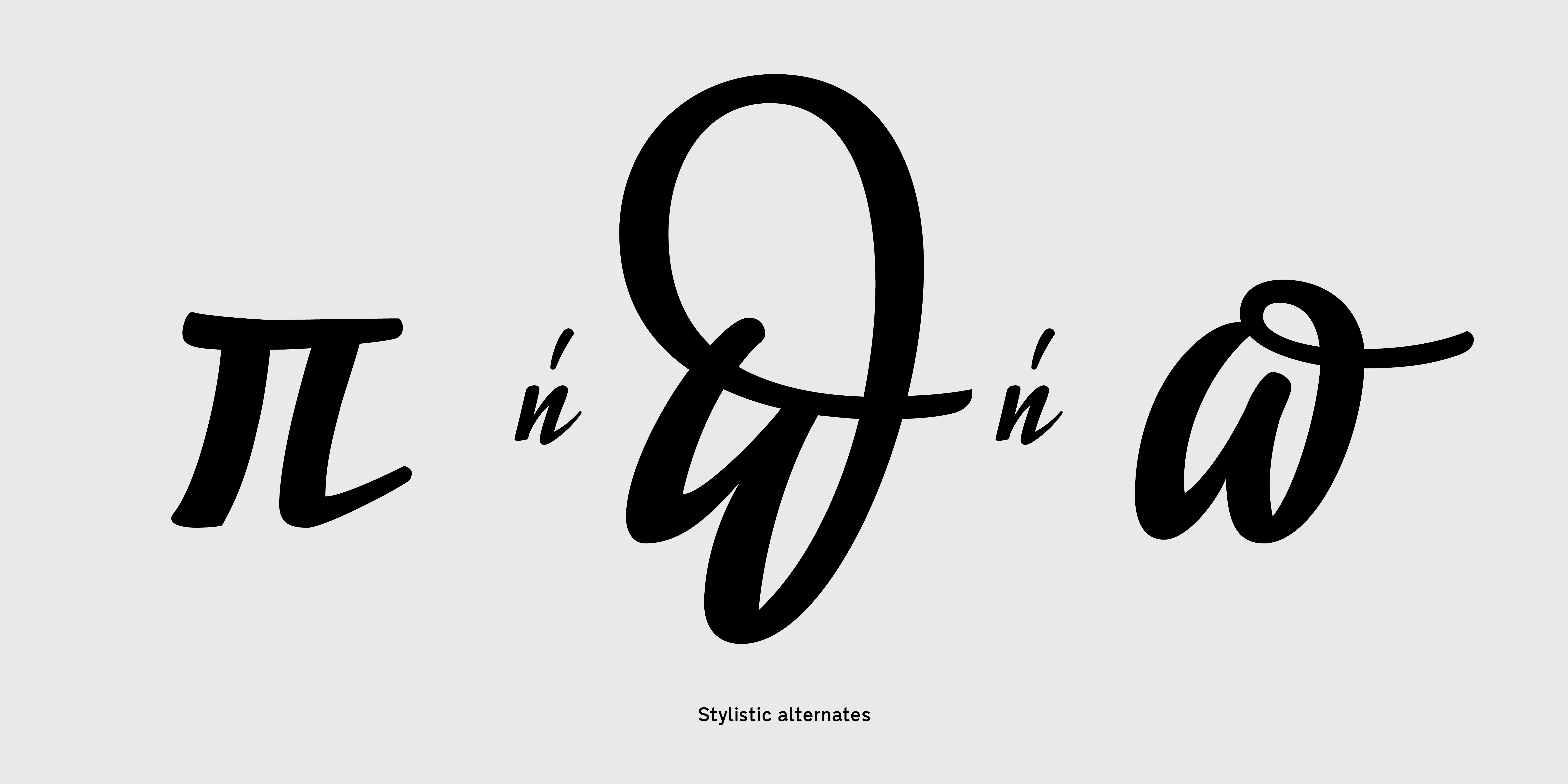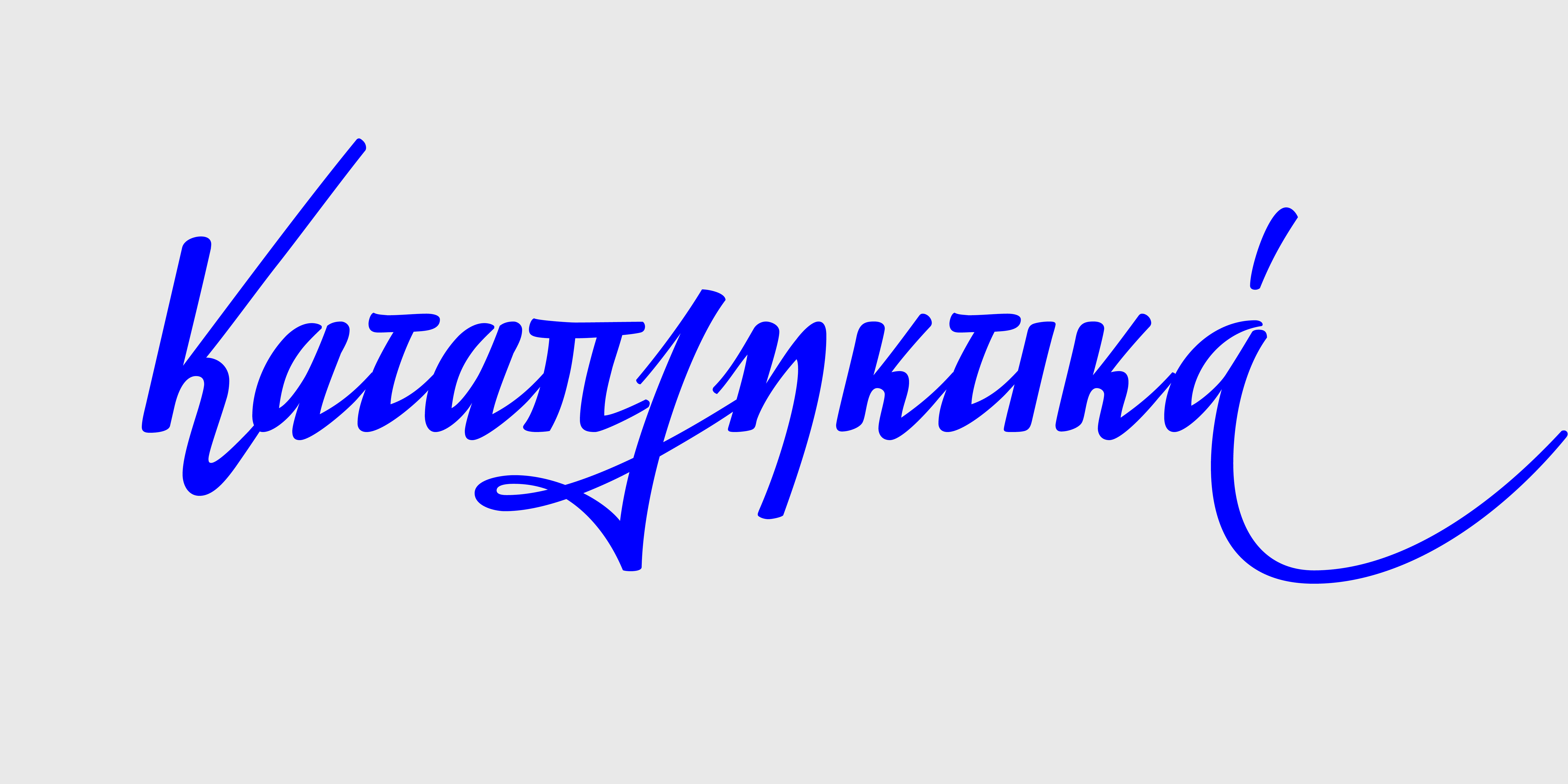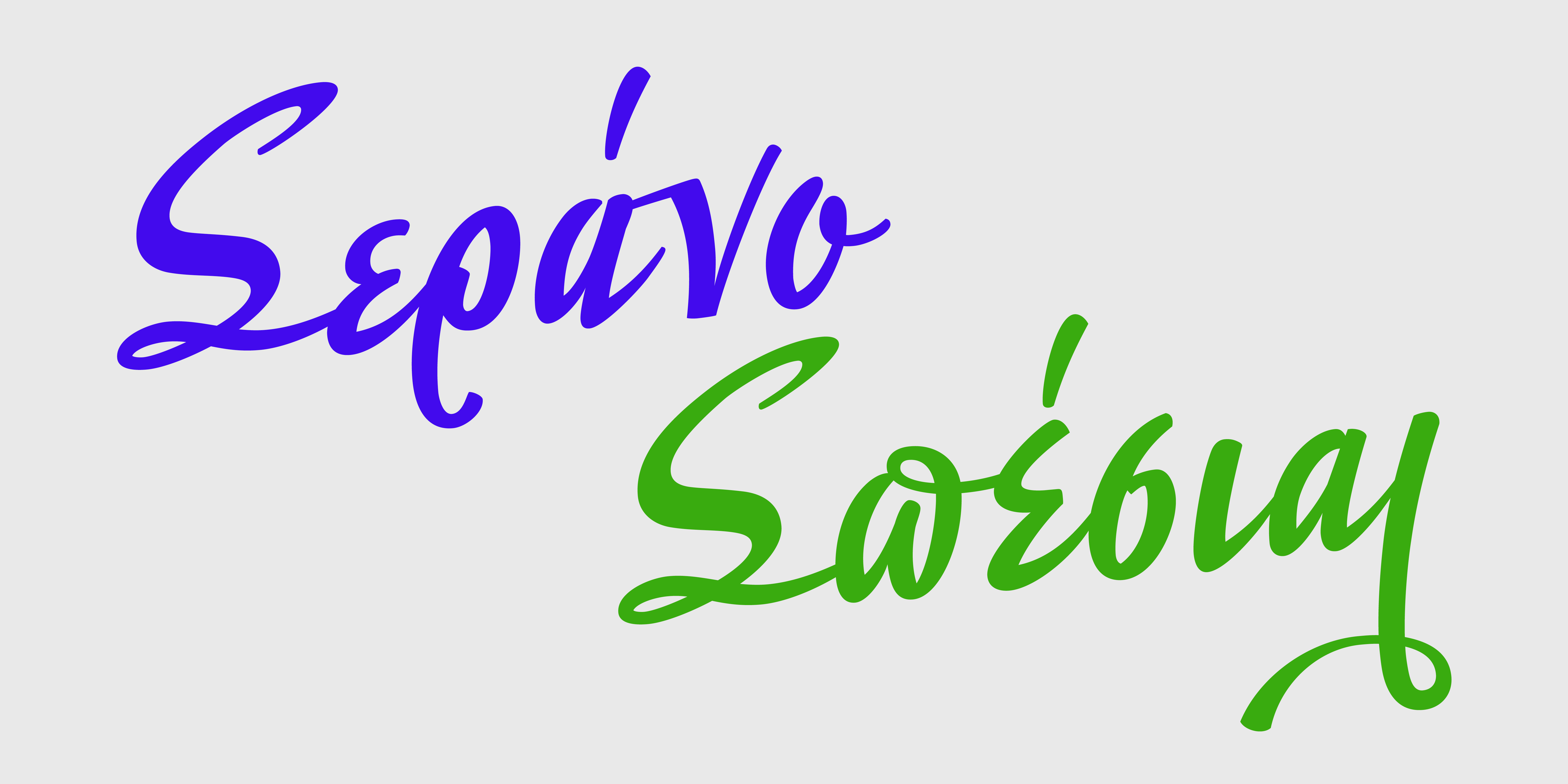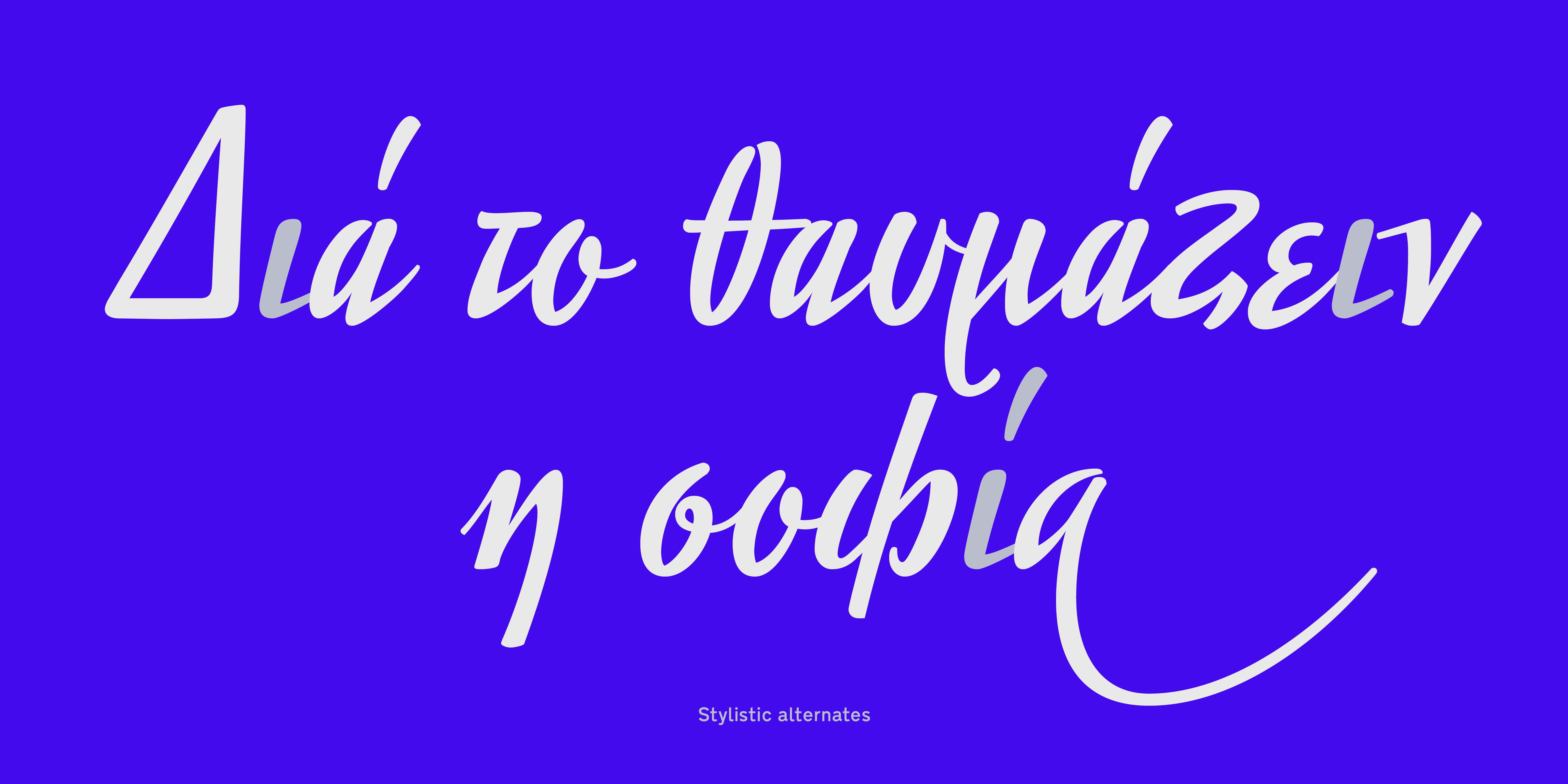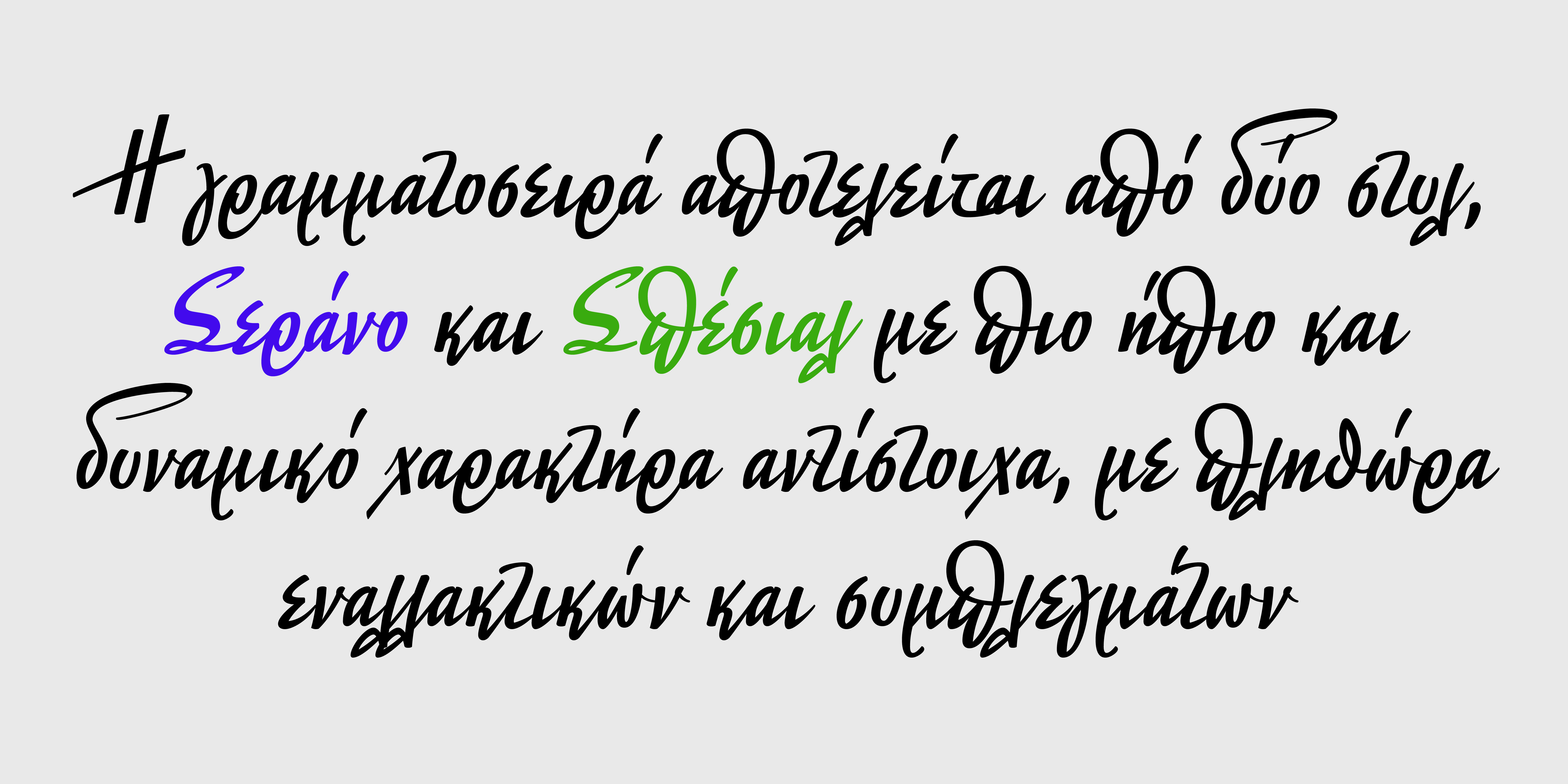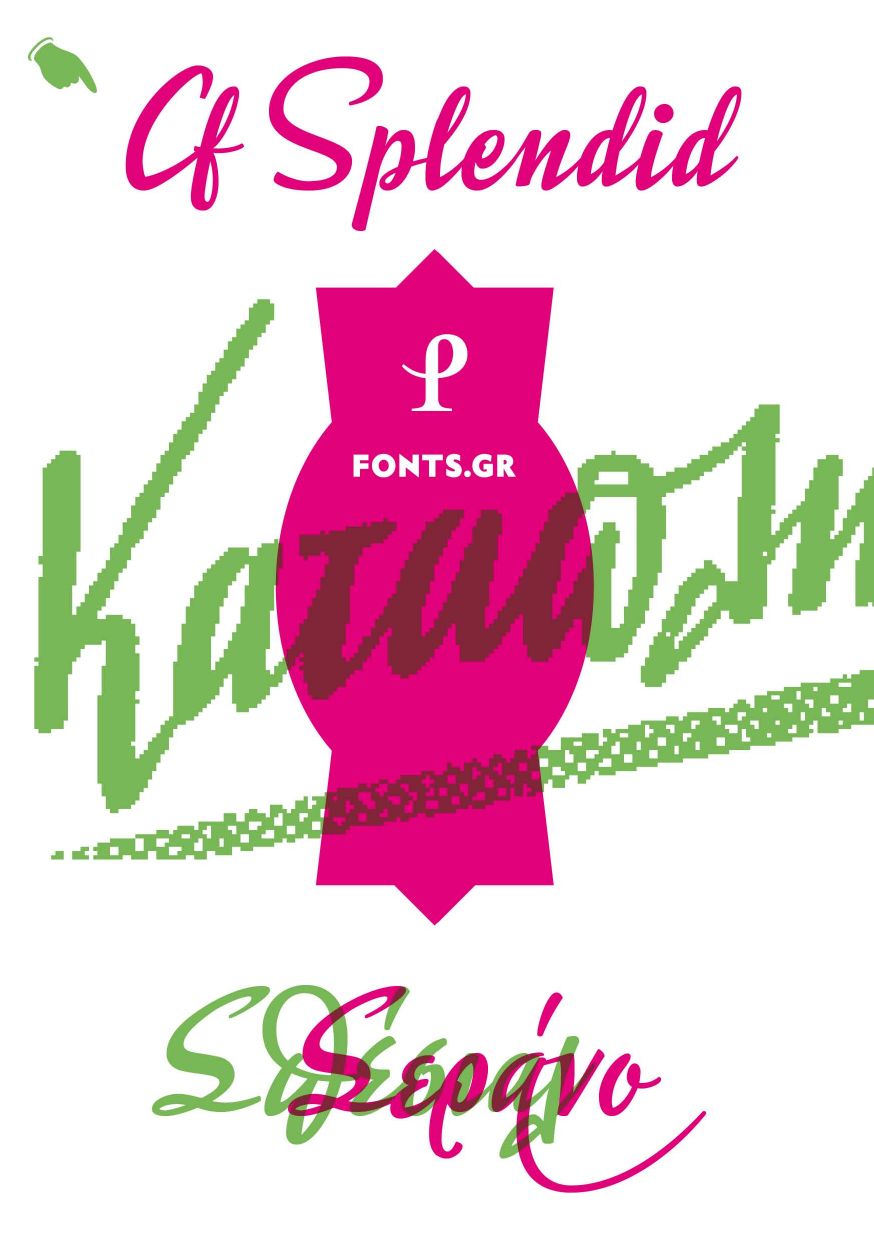
Splendid
Η CF Splendid είναι ίσως η πιο χαρακτηριστική γραμματοσειρά του Στέλλα Πρότζεκτ. Αντλεί έμπνευση κυρίως από τα διαφημιστικά σλόγκαν στις ρεκλάμες των δεκαετιών του ’50 και του ’60. Καθόλη τη διάρκεια της μελέτης μας πάνω στο υλικό που εξετάζαμε, ξεχώριζε μια συγκεκριμένη δυναμική καλλιγραφική γραφή, κυρίως σε διαφημιστικές καταχωρήσεις, περιοδικά και εφημερίδες. Η έντονη εκφραστικότητα της και το παραπλήσιο ύφος της από εικόνα σε εικόνα -είτε διαφήμιζε σοκολάτα, μπύρα, οδοντόκρεμα η οικιακή συσκευή- έδινε την αίσθηση ότι προέρχεται από το ίδιο μαγικό χέρι ενός καλλιγράφου-διαφημιστή, ή έστω, ότι δημιούργησε μία «σχολή» η οποία ακολουθήθηκε και από άλλους ανταγωνιστές. Χαρακτηρίζεται από έντονα εκφραστικό κεφάλαιο πρωτόγραμμα, το οποίο ακολουθείται από «στακάτα» πεζά γράμματα στα οποία ξεχωρίζει ενδιάμεσα ένα ή περισσότερα εκφραστικά γράμματα μεγαλύτερης κλίμακας. Δεν ακολουθούνται απαραίτητα οι τυπικοί βασικοί κανόνες της καλλιγραφίας (γραμμές βάσης και υψών, πάχη γραμμών) αλλά κύριο μέλημα του καλλιγράφου ήταν να τραβήξει την προσοχή του αναγνώστη, μέσω της δυναμικής γραφής και του επιτηδευμένου εντυπωσιασμού. Παρόλο που τα πρότυπα ήταν πολλά, ήταν -σχεδιαστικά- αντικρουόμενα. Έτσι, δημιουργήθηκε πληθώρα σχεδίων μέχρι να επιλεγούν εκείνα που θα ενταχθούν στο αρχείο της γραμματοσειράς. Για την ψηφιακή παραγωγή απαιτήθηκε ένας γενικός επανασχεδιασμός καθώς και η επανασύσταση πολλών χαρακτήρων -κυρίως λατινικών- για τους οποίους δεν υπήρχαν καθόλου δείγματα. Αυτό έγινε με το σκεπτικό του «άναρχου» και χωρίς αυστηρούς κανόνες καλλιγραφικού ύφους, ώστε να εκφράζουν την γενική ιδέα, ενώ παράλληλα όλο αυτό το υλικό έπρεπε να τυποποιηθεί και ομαλοποιηθεί ακολουθώντας τους απαραίτητους τεχνικούς περιορισμούς. Η γραμματοσειρά αποτελείται από δύο στυλ, Σεράνο και Σπέσιαλ, με πιο ήπιο και δυναμικό χαρακτήρα αντίστοιχα, με πληθώρα εναλλακτικών και συμπλεγμάτων. Ο τελικός χρήστης καλείται να τις συνδυάσει μεταξύ τους -ακόμα και στην ίδια λέξη, φράση η λογότυπο» ώστε να παράξει το διαφορετικό ή «τυχαίο» αποτέλεσμα που επιθυμεί. Συνεργασίες: Ευχαριστίες στον Τάσο Βαρυπάτη για την πολύτιμη βοήθεια στην ψηφιοποίηση και τον σχεδιασμό.